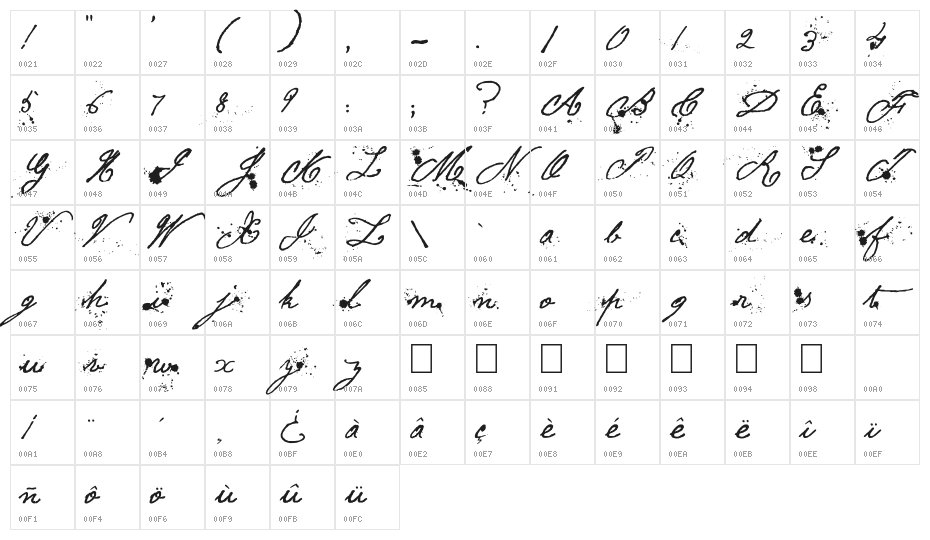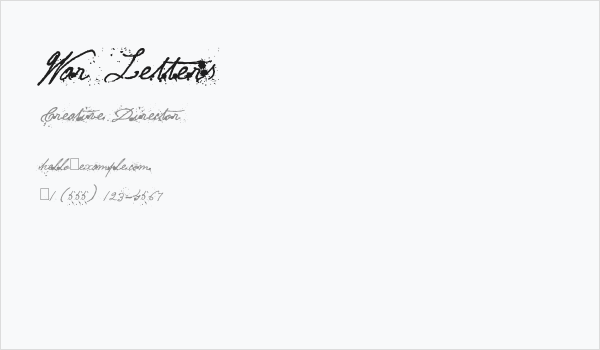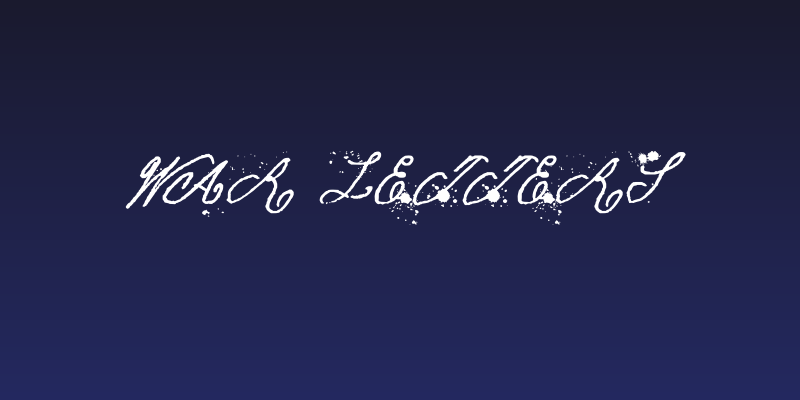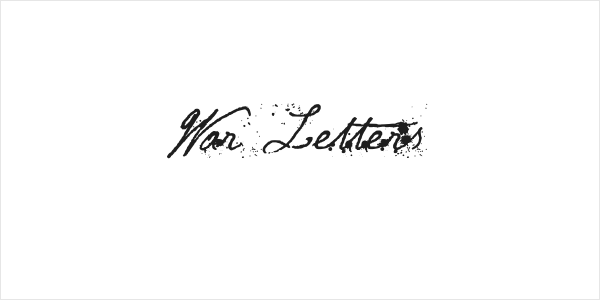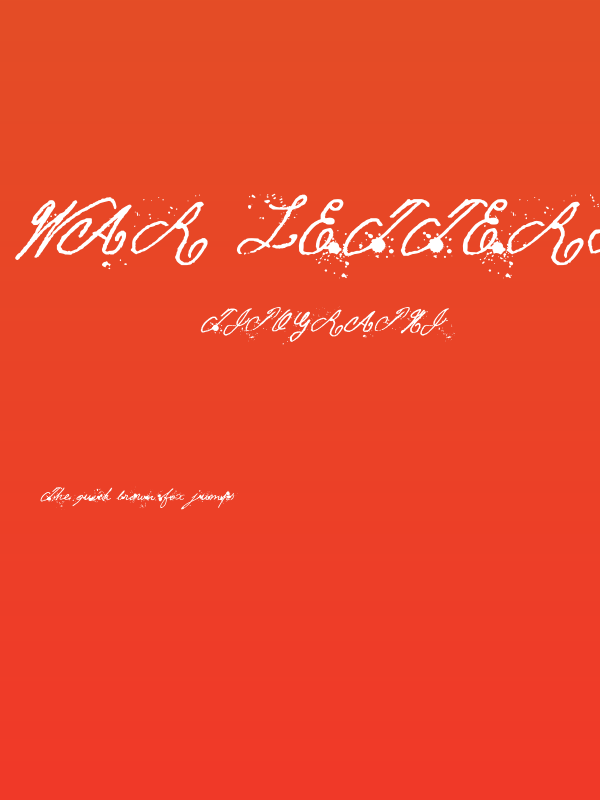
War Letters Font
| Cas d'utilisation | Logos, Artistic projects, Invitations |
| Projets proposés | Ideal for projects that require a personal touch, such as invitations, artistic posters, or album covers. It can also be used in branding for creative industries or in designs that aim to evoke nostalgia or emotion. |